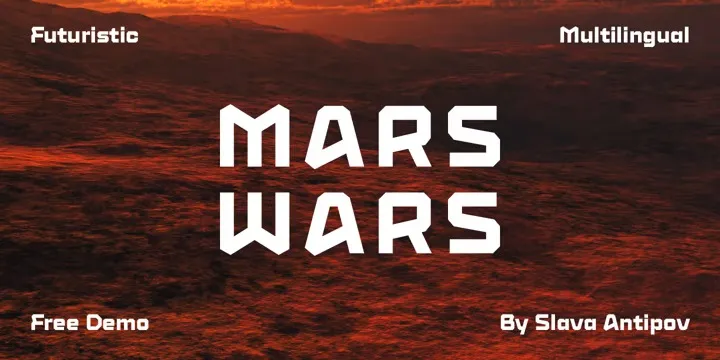
A fonte ‘Mars Wars Font’ é uma elegante tipografia em estilo sans serif, projetada por Slava Antipov. Este tipo moderno traz uma sensação de simplicidade e clareza que é perfeitamente adaptável para usos visuais variados. Com linhas tecnológicas originais e um toque amigável, a fonte ‘Mars Wars Font’ se destaca especialmente em aplicações como logotipos, embalagens, outdoors e muitas outras. Seu design intuitivo e minimalista o torna uma opção ideal para designers que buscam uma tipografia moderna e forte capaz de transmitir força visual sem perder a simplicidade elegante. Ideal tanto para uso digital quanto impresso, a ‘Mars Wars Font’ oferece uma solução versátil para qualquer projeto gráfico em busca de um design chamativo e clean.